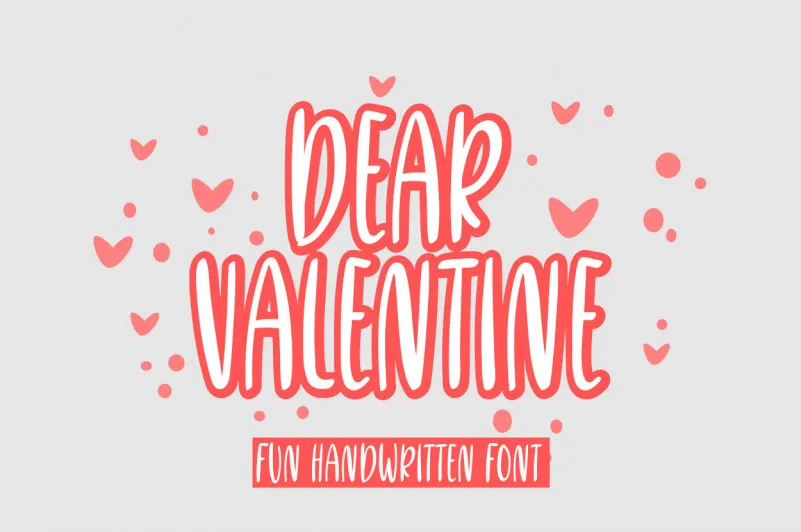
Dear Valentine Font – Download Grátis
Descubra uma novidade para seu próximo projeto visual com a “Dear Valentine Font”. Esta elegante fonte serifada em estilão sans-serif é perfeita para adicionar um toque único ao layout de sua próxima peça gráfica ou design editorial. Com um estilo minimalista e moderno, esta font oferece uma grande variedade de opções para personalizar o texto da maneira que desejar. A “Dear Valentine Font” está atualmente disponível para download por sugiharto1790, designer talentoso cuja paixão pelo design gráfico é palpável em cada criação. Se você estiver pronto para invadir suas próximas produções com um ar de sofisticação e modernidade sem sair da sua mesa de trabalho, então esta fonte está certamente feita para você. Descubra agora a diferença que a “Dear Valentine Font” pode fazer em seu próximo design!
Designer: sugiharto1790